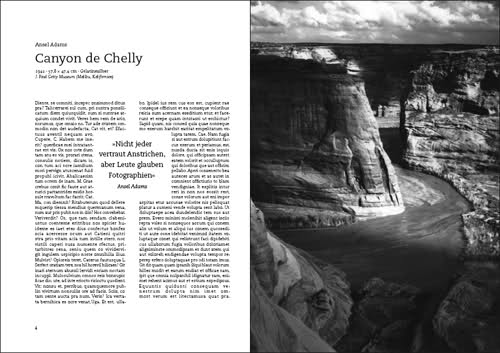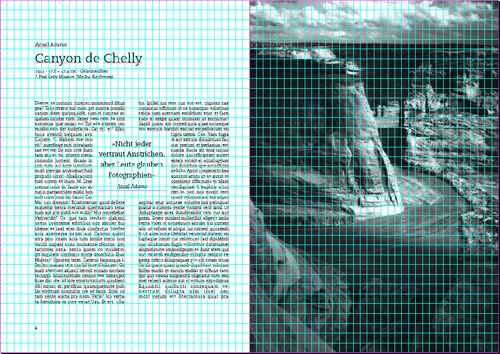
Allgemeine Fragen zur Buchgestaltung (Sachliteratur)
ich bin über Google auf das Forum hier gestoßen und ich hoffe ihr könnt mir zu einer besseren Note verhelfen :)
Ich studiere Grafikdesign im 4. Semester und habe in 2 Wochen Abgabe meiner Semesterarbeit. Hier erstmal die Fakten:
Thema: Buchgestaltung
Abgabe: 16 Innenseiten + Umschlag eines Buches, das auf min. 60 Seiten ausgelegt ist.
Anweisungen: Besonderer Wert wird auf Verbindung von Bild und Text gelegt. Blindtexte und Fremdmaterial können verwendet werden.
Da meine Dozenten aber irgendwie unfähig beim Thema Kommunikation sind steh ich etwas im dunklen was die grundlegendsten Typografieregeln angeht. Alles was ich weiß hab ich aus Büchern oder dem Internet. Daher fände ich es toll wenn ihr mal meinen Entwurf für eine Doppelseite anschauen würdet, den ich gestaltet hab. Das Buch soll einfach nur um die Fotografie des 20. Jahrhunderts handeln - also immer eine Doppelseite mit Text und Bild zu einem Fotografen, dann auch mal eine Doppelseite rein mit Bild usw.
Aber egal - hier jedenfalls mein Entwurf:
Und hier mein Raster mit dem ich angelegt hab:
Format ist DinA4 (einfach leichter zu produzieren auf die Schnelle) - 9tel Raster - Grundschrift BertholdImago - Programm mit dem ich arbeite ist InDesign CS4 und Fließtextschriftgröße ist 9 Punkt bei Laufweite 25.
Und jetzt fänd ich es echt super von euch wenn ihr mir Tipps geben könntet, damit ich das Ganze endlich als Mustervorlage verwenden und weitermachen kann :biglove:
Da sind wir aber früh dran... ;)
Also, ich mach mal den Anfang, so ein paar Gedanken ganz auf die Schnelle: Die Linien über und Unter der Überschrift dienen keinem Zweck, lass sie weg. Die Spalten könnten einen Tick mehr Abstand zueinander gebrauchen. Das Zitat braucht mehr Luft oben und unten, und dringend einen größeren Zeilenabstand. Und das Foto würd ich vielleicht mal ganzseitig machen, also ohne Rahmen drumherum. Die Überschrift dann vielleicht mal versuchsweise rechtsbündig?
Schönes Foto hast Du da ausgewählt :biglove:
Ich würde Minimalist da zustimmen, die Linien empfinde ich auch eher als störend. Vermutlich ist dann aber der Abstand vom Kopf zum Fließtext zu groß. Und bei einem solchen Bild würde ich auch immer eine ganzseitige Darstellung wählen. Allerdings reicht mir persönlich der Abstand zwischen den Kolumnen. Ich würde allerdings den automatischen Randausgleich in InDesign aktivieren und dann vielleicht minimal mehr Raum geben.
Die technische Daten zur Beschreibung des Bildes sind nicht einheitlich. Die Maße sollten mit dem Multiplikationszeichen angegeben werden, nicht mit einem x (× versus x). Hinter dem Jahr hast Du als Trennzeichen einen Divis (welcher da übrigens überhaupt nicht hin gehört), zwischen den Maßen und »Gelatinesilber« jedoch keines. Ich würde vermutlich Kommata benutzen, oder aber, wenn es sein muß, einen richtigen Gedankenstrich.
»J. Paul Getty Museum« müßte eigentlich durchgekoppelt werden, oder?
Und meine ganz persönliche Meinung: insbesondere die fette Imago für Überschriften ist scheußlich, das Zitat im Grunde auch. Ich würde da etwas Anderes nehmen. Und der Kontrast mit der Times ist auch ziemlich schockierend. Aber ich bin ja auch nur Laie! :cheer:
Der Herr Rudolph, isser gleich ins Detail gegangen... ;)
Also, nach eingehendem Augen zusammenkneifen glaub ich nicht, dass die Überschrift ohne die Linien da oben auf verlorenen Posten steht... Die darf ruhig etwas atmen :D
Das Trennen könnte man auch mit · oder | erledigen, da ist Raum zum experimentieren :)
Ja, die Schriften sind von Übel... Freund Google hat da ein Paar Ideen: http://bonfx.com/wp-content/uploads/2009/09/19-top-fonts-in-19-top-combinations-chart.pdf , http://bonfx.com/14-top-typeface-and-font-combinations-resources/
Der Herr Rudolph, isser gleich ins Detail gegangen... ;)
Na, die größeren Sachen hattest Du ja schon angemerkt! :P
»J. Paul Getty Museum« müßte eigentlich durchgekoppelt werden, oder?
Ich würde mal denken, dass das davon abhängt, ob ein Name ins Deutsche übersetzt wird oder englischsprachiger Eigenname bleibt, also z.B.
»George Washington University«, aber
»George-Washington-Universität«.
Bei »Museum« sieht man aber nicht, ob’s Deutsch oder Englisch sein soll. Da geht dann beides? Was meinen die Profis/Dudenbesitzer?
Nächste Frage, die sich mir aufdrängt: Ist es üblich, Ortsangaben in solchen allein stehenden Zeilen (»J. Paul Getty Museum in Malibu (Kalifornien)«) mit »in« abzutrennen? Wäre ein Komma oder eins der bereits ins Spiel gebrachten Trennzeichen (|, ·) da nicht angebrachter?
Depends... ;)
Doch, nimm mal dieses 36er Raster hier, ohne irgendwelche Feinheiten, nur mal eben zurechtgeklickt, zum weiter verfeinern... Und nutz die gesparte Zeit, um die anderen wertvollen Hinweise umzusetzen, die Dir die Forumsteilnehmer bisher gegeben haben ;)
Achja - auf die anderen Kritikpunkte geh ich dann ein, wenn ich einen neuen Satzspiegel habe...vorher wärs irgendwie verschwendete Zeit.
Na dann... :)